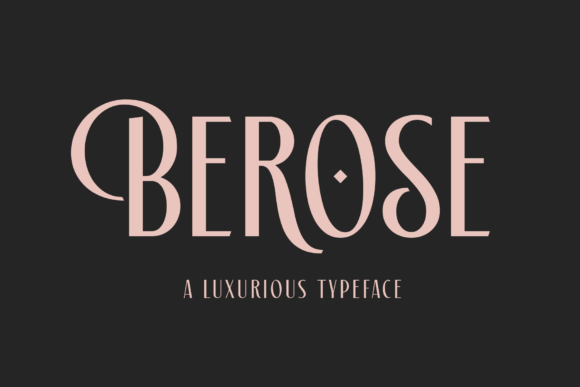
Бероза - это роскошный шрифт с высоким контрастом.
Шрифт Бероуз выполнен в двух стилях: регулярный и наклонный с некоторыми альтернативными персонажами, элегантный и динамичный, он идеально подходит для романтических нюансов, таких как свадебные приглашения, обложки, названия фильмов, цитаты, логотипы, вывески и многое другое.